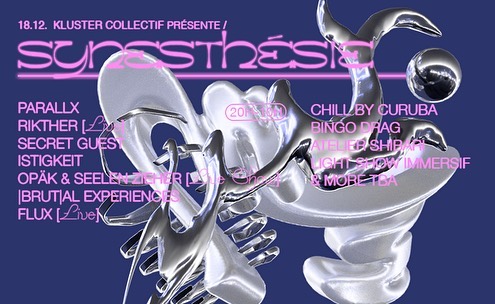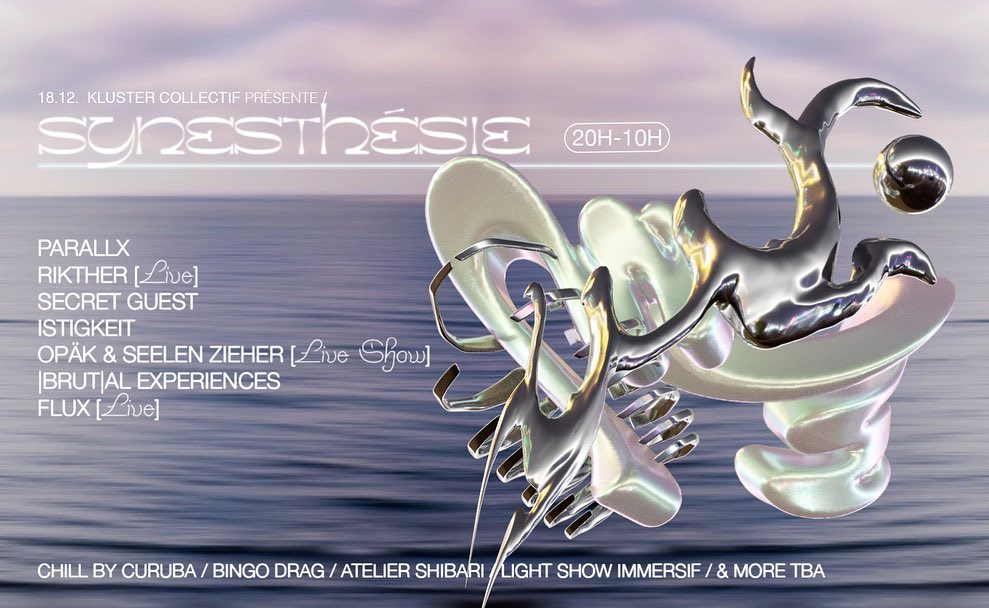
Genese
Genese 是一款具有强烈现代设计气质的实验型展示字体,以几何结构重塑传统字母形态,通过简洁的线条、独特的比例关系以及高度统一的视觉系统,打造出兼具未来感与艺术表现力的字体风格。字体在保持基础识别性的同时,大胆突破常规字母结构,使文字本身成为一种具有视觉张力的图形元素。
从字形设计来看,Genese 最大的特点在于对英文字母进行了几何化重新构造。设计并非简单使用规则几何图形替代传统笔画,而是在曲线、直线与空间切割之间寻找平衡。部分字母采用极简化的轮廓处理,减少多余细节,使整体结构更加轻盈、精准。字母之间保持统一的设计逻辑,在大小写混排时能够形成自然连贯的视觉节奏,呈现出类似未来科技界面的秩序感。
从视觉表现来看,Genese 具有明显的先锋艺术与未来主义气质。字体线条纤细流畅,结构开放而富有空间感,在海报、展览视觉、音乐活动、时尚品牌等场景中能够展现较强的表现力。相比传统几何字体的理性与冷峻,Genese 通过部分特殊细节处理增加了独特性,例如字母装饰元素、非传统连接方式以及精巧的局部变化,让整体视觉不会陷入单纯机械化,而是呈现出更具实验性的设计语言。
从排版效果来看,Genese 更偏向于标题展示用途。其纤细的线条和独特的字形结构,在大尺寸排版时能够充分展现字体细节,适合用于品牌标识、活动海报、艺术展览、时尚宣传、音乐视觉以及创意包装等需要强调视觉个性的设计项目。搭配简洁背景或高对比度色彩时,能够进一步突出字体本身的形式美感。
从整体风格来看,Genese 将现代几何设计、未来主义视觉以及实验字体语言结合在一起。它并不追求传统字体的通用性,而是通过独特的造型探索文字作为视觉符号的更多可能性。对于希望打造年轻、新锐、科技感或艺术化品牌形象的设计项目而言,Genese 提供了一种具有辨识度的字体选择。
Genese 是一款以几何重构为核心的现代展示字体,通过简洁线条与独特字形比例打造出未来感十足的视觉风格。它兼具理性结构与艺术表达,适合用于品牌设计、海报排版、音乐视觉、展览设计等强调个性与创新的创意项目。